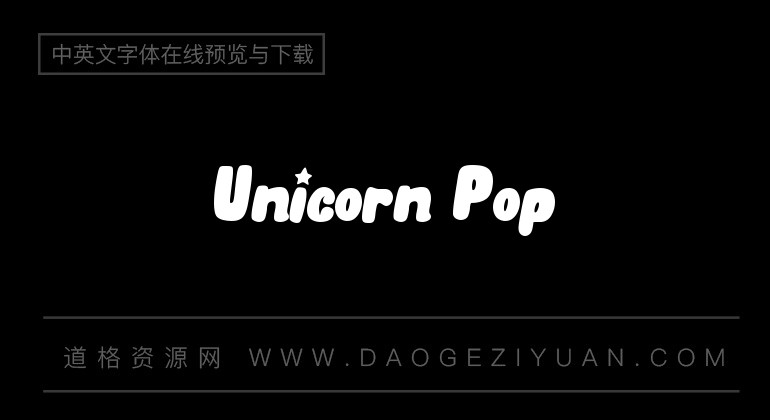
Unicorn Pop
? Unicorn Pop 字体是一款漂亮可爱的英文字体,它以抓住年轻人的心而闻名。Unicorn Pop 的字体具有明亮色彩,清晰的线条,夸张的形状,以及一种活泼可爱的氛围。这款字体适合为网站,印刷品,海报,T恤,标志等创造出一种有趣的,活泼的,可爱的气氛。
Unicorn Pop是一款非常不错的手写艺术字体,具有很好的视觉感,适合于文化类的宣传设计、商业类品牌的广告和产品包装设计以及个性化文字排版等较多场景。